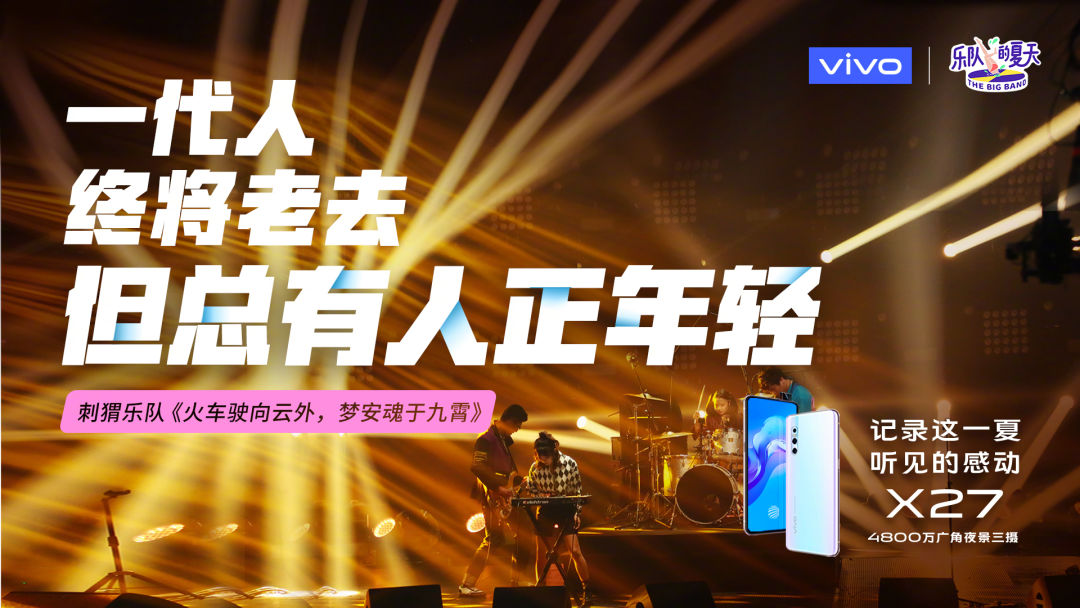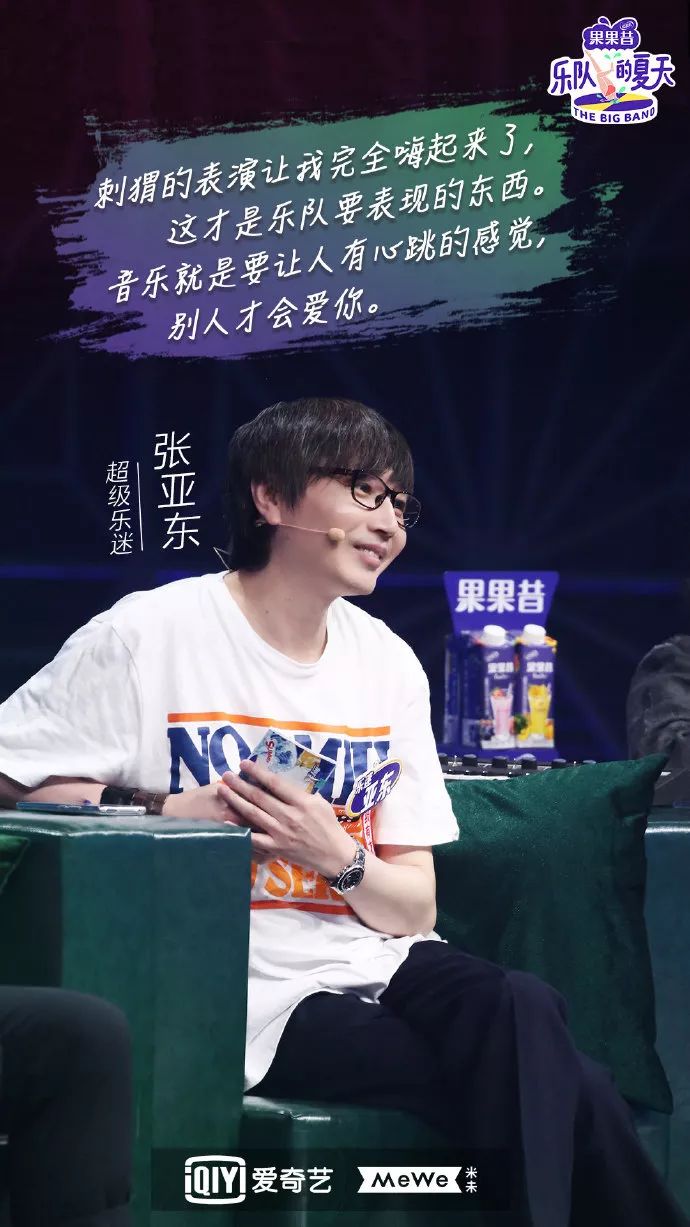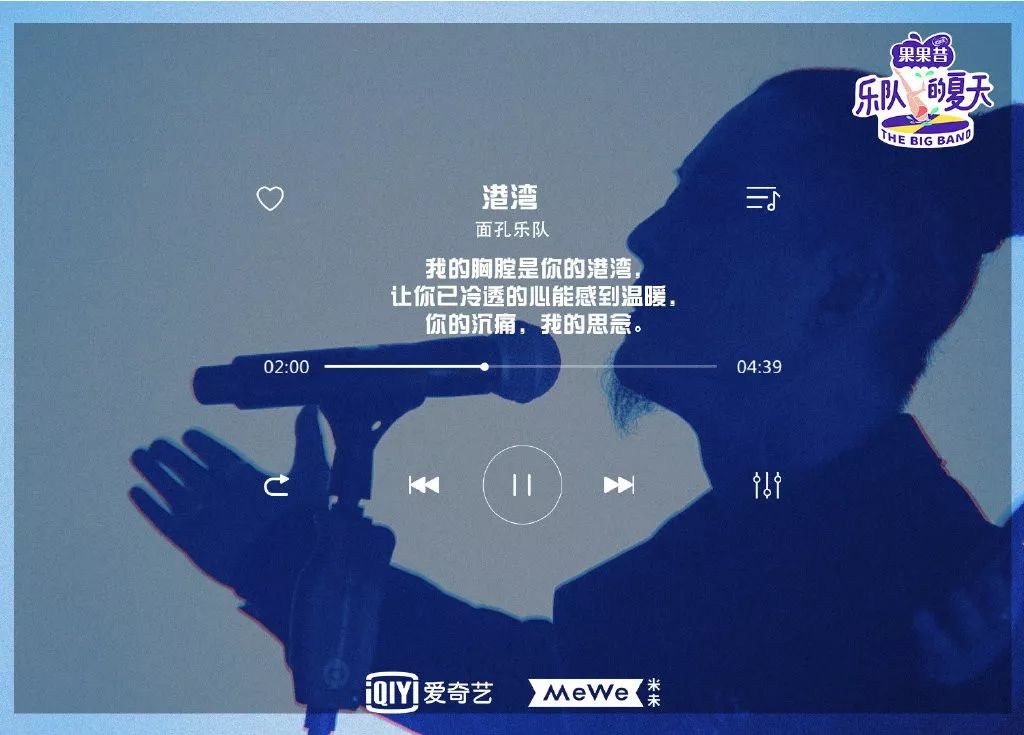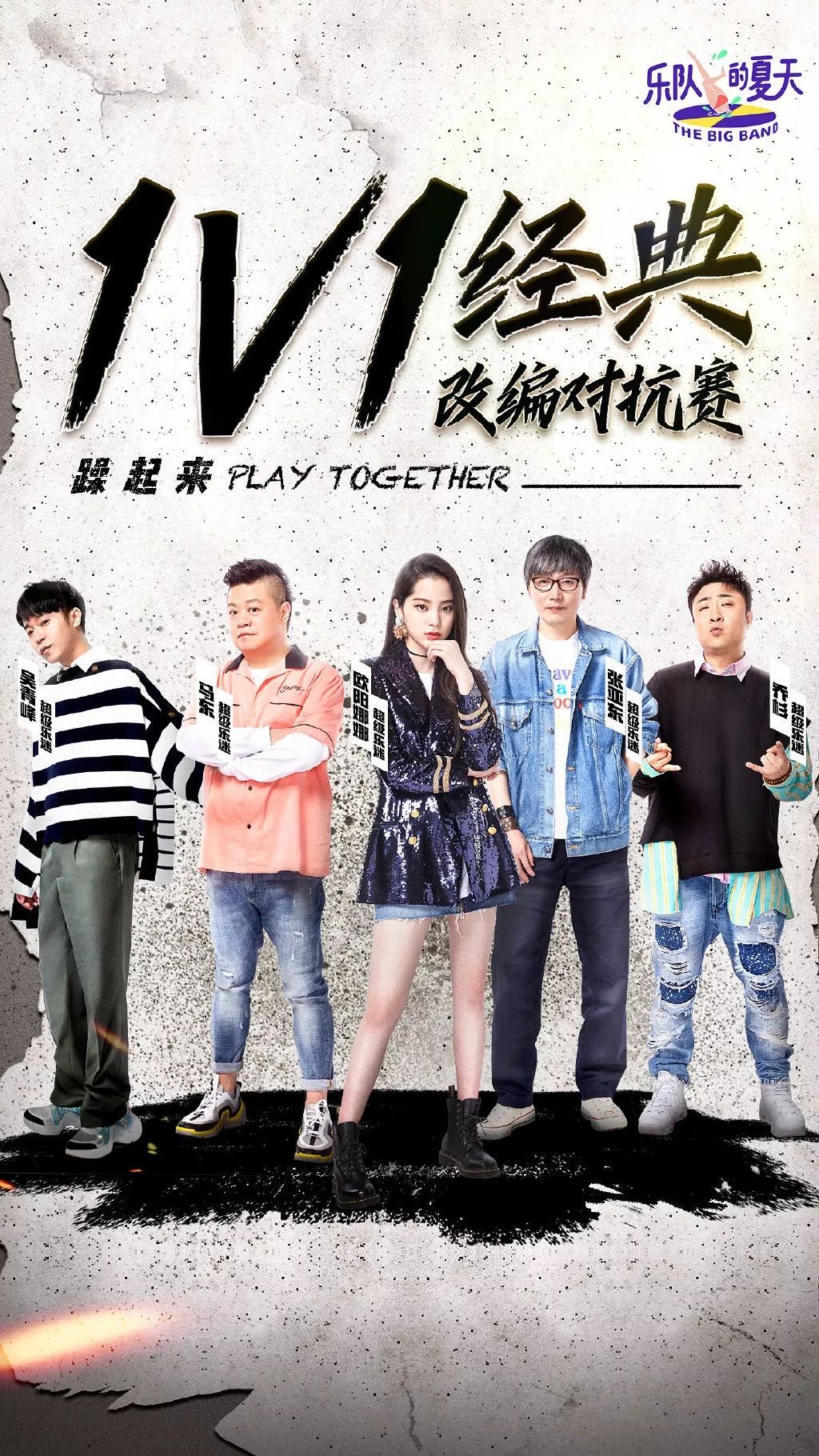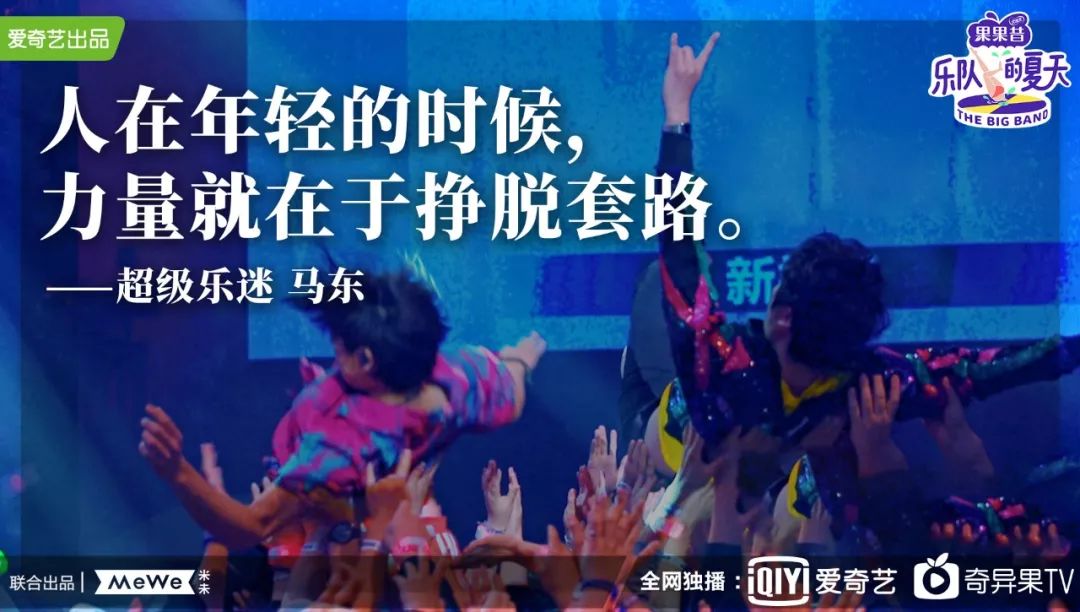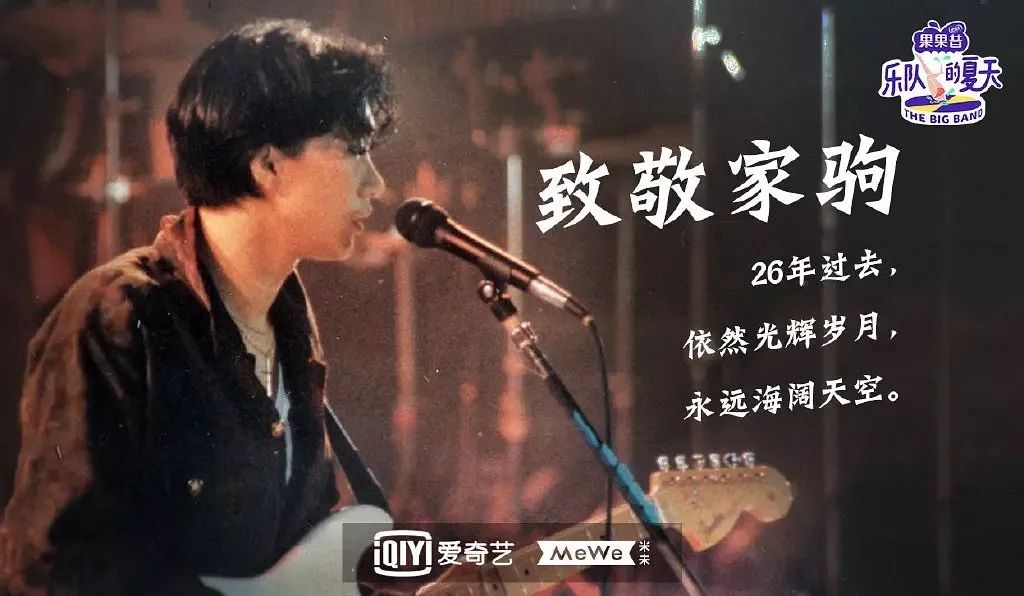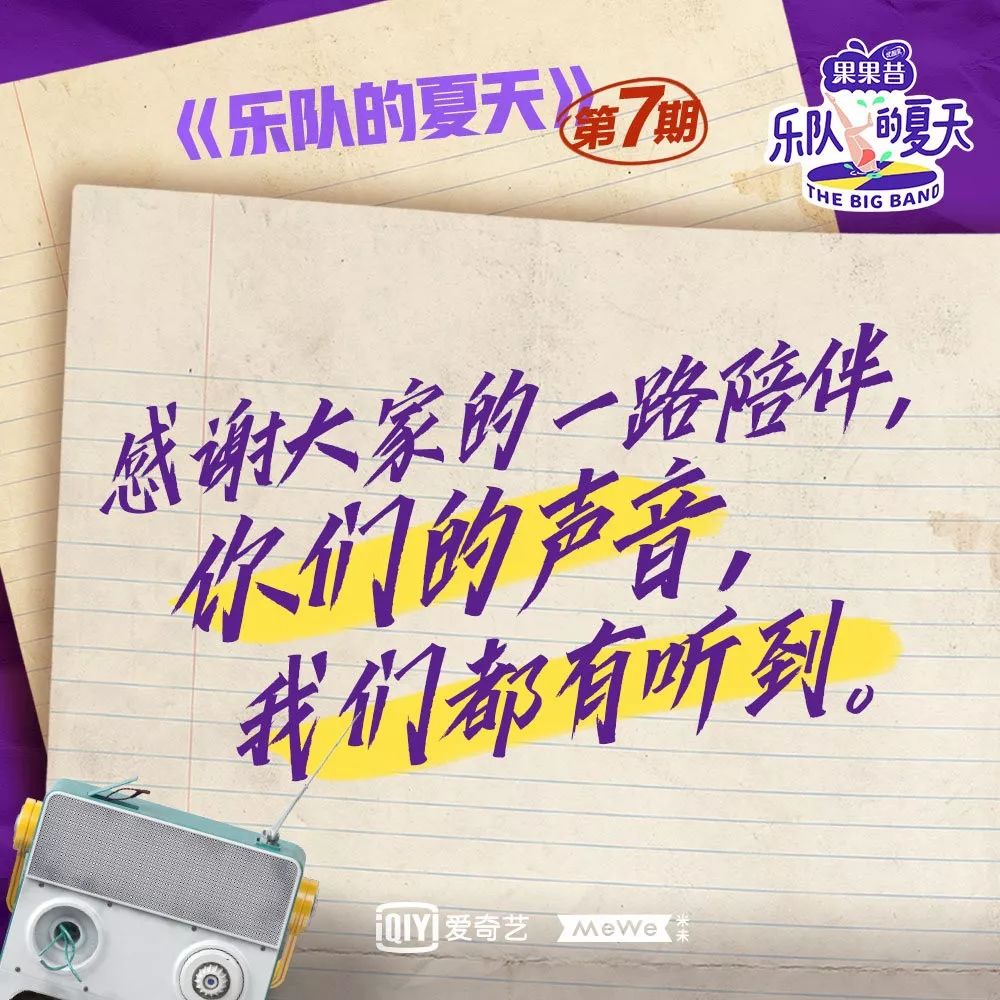
乐队的夏天为啥能把人看哭?幕后的秘密都在这~
这边柚子刚追街舞追得欲罢不能,另一边《乐队的夏天》又燃了,豆瓣评分8.6。
可我看了一点,就发现画风不对,怎么变成哭综了~
再品品这句话,妈呀,泪崩了……
▲汉仪力量黑
连我这个对乐队完全不感兴趣的人,也被那些金句点燃了,特别是张亚东,你怕是被唱歌事业耽误的情感博主吧!
▲华康翩翩体
▲汉仪尚巍手书
▲汉仪意宋
不止他,乐队的每段感言、每句歌词、每个回忆,都是一个大写的戳戳戳……
▲华康新综艺
▲汉仪书魂体
所以我就懂了,音乐不在外表,而是内心的情感表达,这种感染力会让你重新热爱一切。
▲思源宋体
汉仪力量黑
除了文案,乐队在设计上也加入了小心思,比如综艺大火的汉仪力量黑,别人可能都是突出力量感,power!
它却用小阴影,增加精致感,看起来又燃又有情怀~
做起来也很简单,就是用渐变的小矩形,加在笔画间,形成透气感。
英文也是一样,还有点折纸的效果~
不过乐队还得“躁起来”。那更炸裂的尚巍手书、天宇风行,就必不可少了。
▲汉仪天宇风行体
▲汉仪尚巍手书
其实乐队的夏天,就是一个披着音乐综艺的戳心人,让每个人都找到曾经热血的自己……